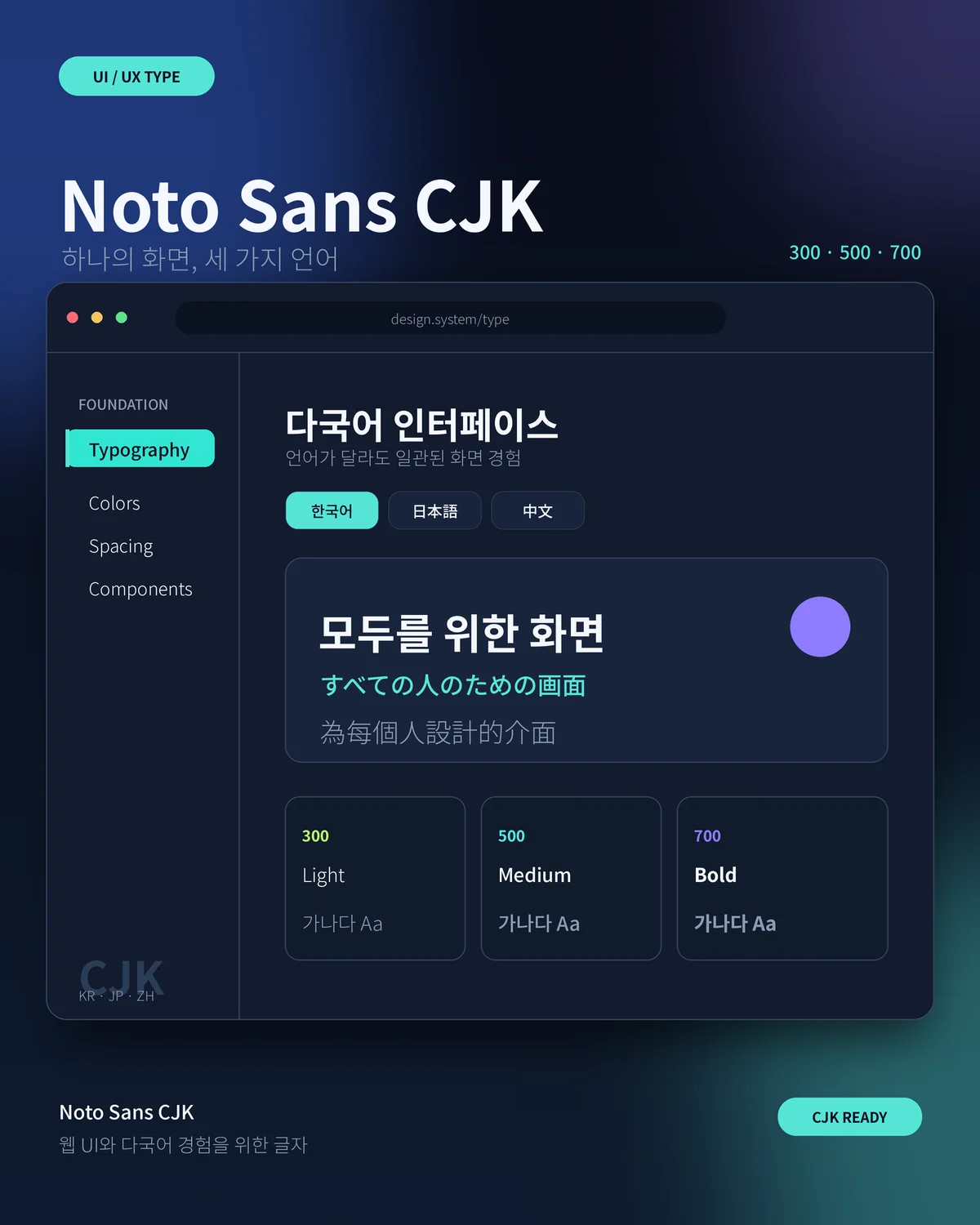
글꼴은 단순한 장식이 아니라 목소리입니다. 같은 문장도 어떤 폰트로 담느냐에 따라 다정하게, 단단하게, 혹은 우아하게 들립니다. 화면과 인쇄물 모두에서 안정적으로 읽히는지 직접 확인해 보세요.
Noto Sans CJK KR — 추천 용도
- 인스타 · 카드뉴스 8위 — 한·중·일 문자를 하나의 체계로 아우르며 균형 잡힌 자형을 구현한 산스체
- 문서 · 웹 본문 7위 — 한·중·일 문자를 하나의 체계로 아우르며 균형 잡힌 자형을 구현한 산스체
- 리플렛 · 인쇄물 2위 — 9가지 굵기에 한·중·일 문자를 한 체계로 갖춰, 외국어를 함께 적는 안내문·메뉴판에서도 글자가 어긋나지 않습니다.
- 쇼핑몰 상세페이지 14위 — 한·중·일 문자를 하나의 체계로 아우르며 균형 잡힌 자형을 구현한 산스체